康有为行书《泰山》诗轴是由清朝时期康有为所作的行书书卷。尺寸:151.2×40.5厘米。康有为,清末著名书法家和书法理论家。康有为自幼学书受家庭熏陶,早年习王、欧、颜、苏、米诸大家的书艺。中年之后,倡导北碑,博览多种金石碑刻,创立出独特 "康南海体"。
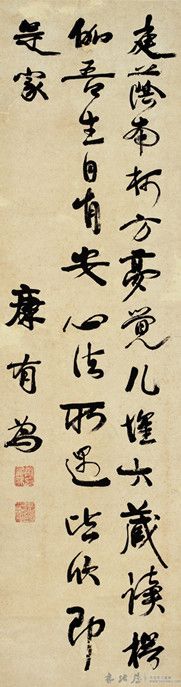
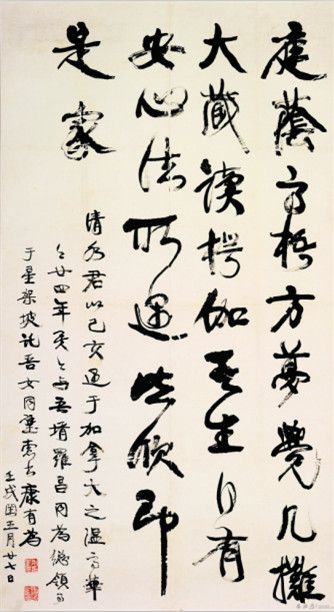
后人了解康有为,大多基于“戊戌变法”。康有为在书法艺术方面所作的贡献,绝不比他在政治舞台上的作为逊色。他不仅是位杰出的政治家,也是继阮元、包世臣后又一大书论家。他于光绪十五年(1889年)所著的《广艺舟双楫》从理论上全面地系统地总结碑学的一部著作,提出“尊碑”之说,大力推崇汉魏六朝碑学,对碑派书法的兴盛有着极其深远的影响。